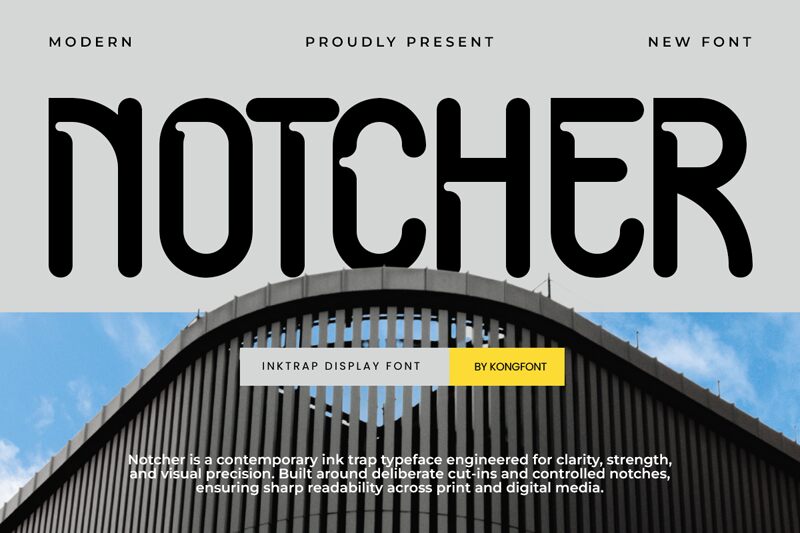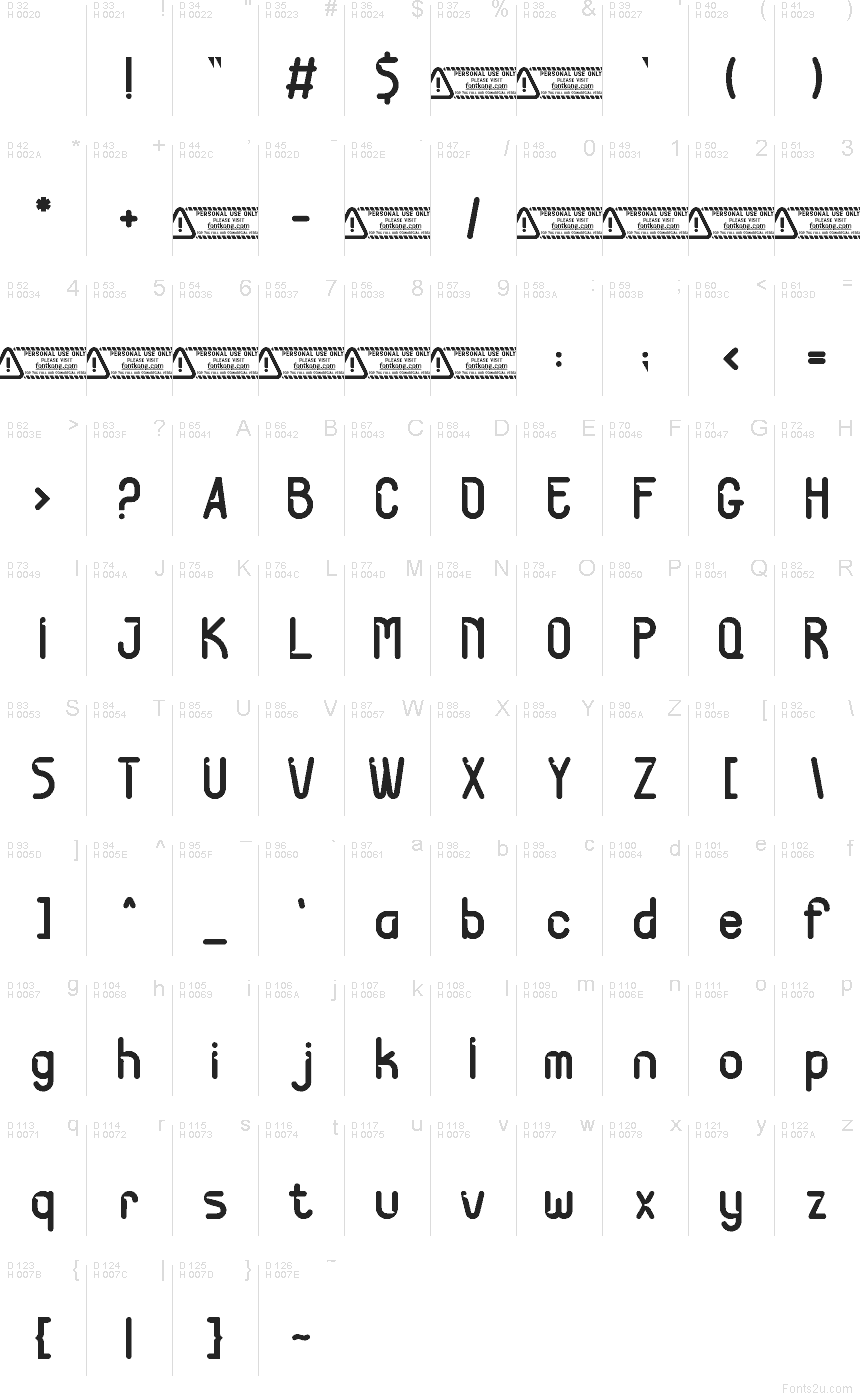
Notcher, créé par Typeface Kong Font, est une police d'affichage rétro gratuite aux formes douces et arrondies, offrant un rythme compact et incurvé. Ses caractères présentent une esthétique lisse et découpée, conférant à la ligne une allure stable et légèrement nostalgique sans jamais tomber dans l'ornemental.
Notcher est idéale pour les titres d'affiches, les logos, le packaging, la signalétique et les accents éditoriaux courts, car ses formes simples conservent une personnalité distincte. Cette police gratuite convient parfaitement au branding rétro, aux menus de cafés et aux visuels pour réseaux sociaux lorsque vous recherchez une typographie de titre à la fois chaleureuse, bien structurée et facile à marier avec un texte courant.